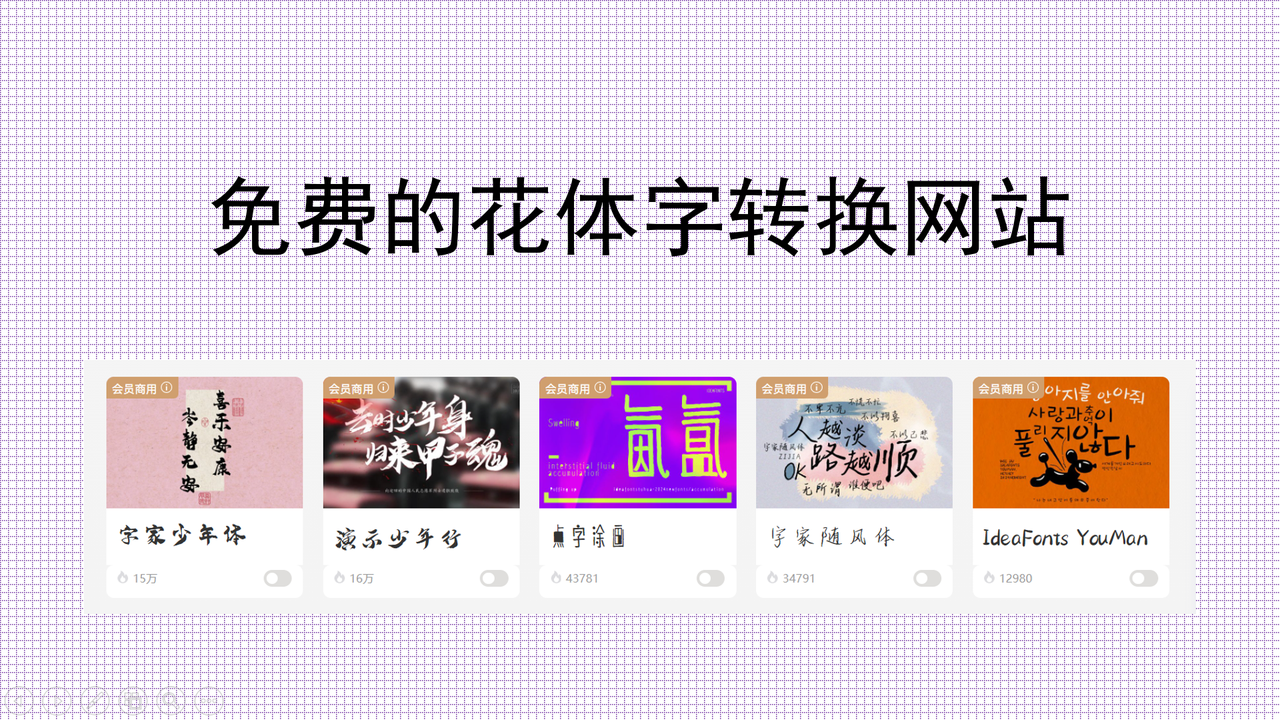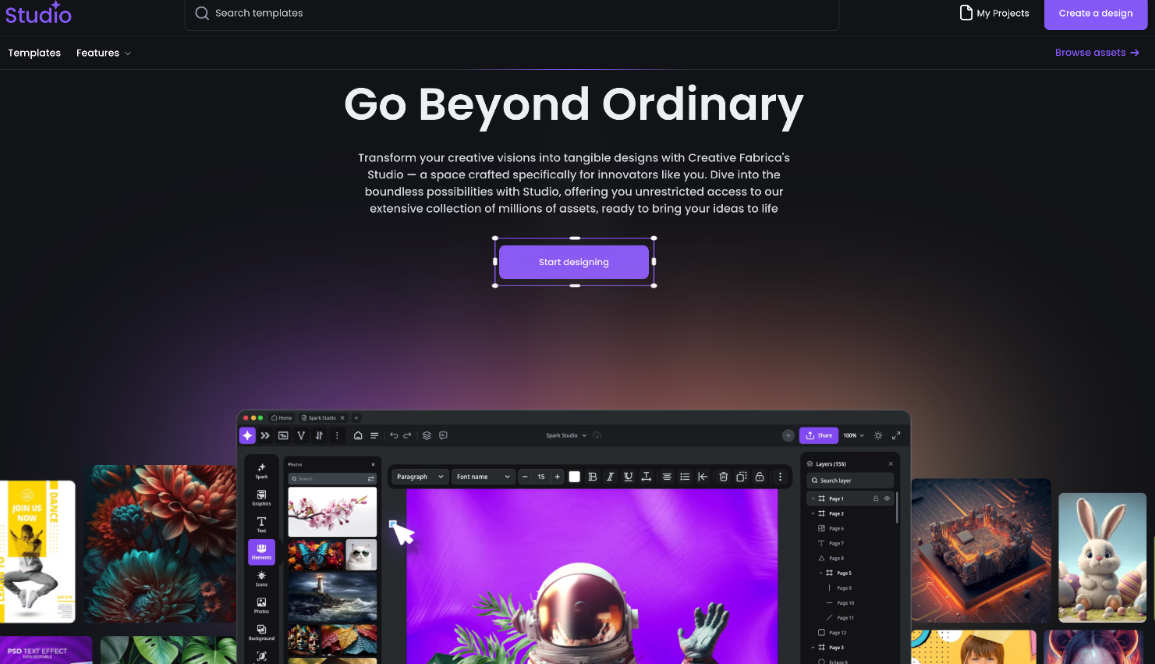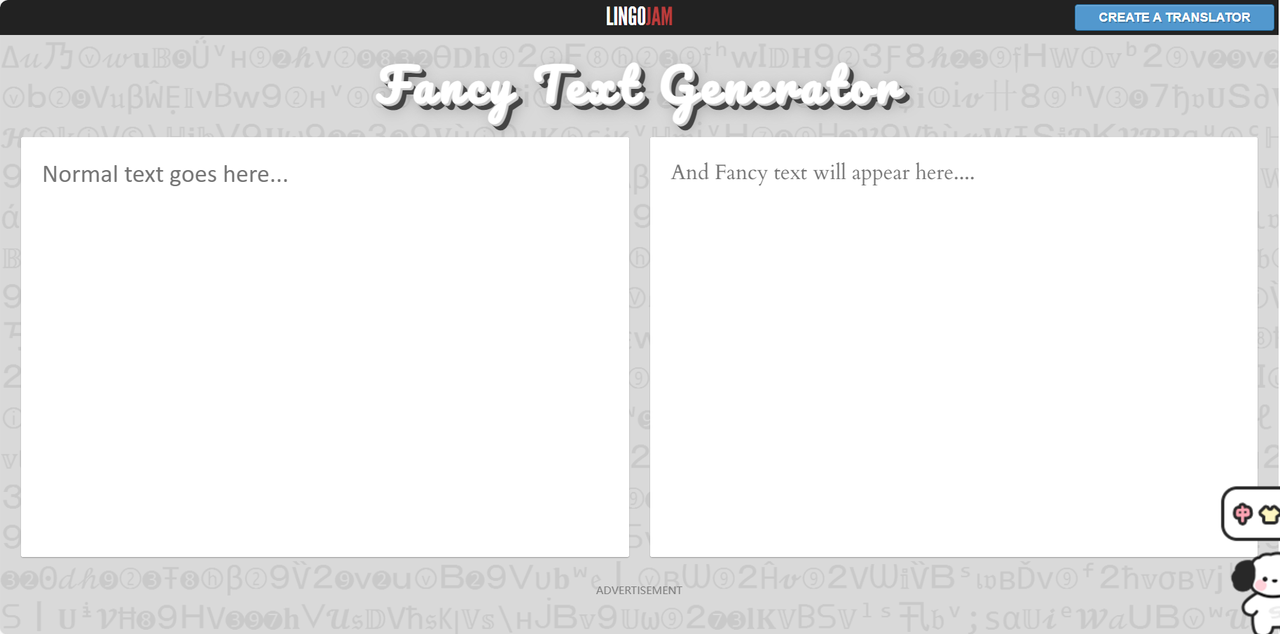
免费花体字转换网站,高颜值花体一键生成无版权
在社交媒体盛行的时代,个性化的文字表达已经成为彰显自我风格的重要方式,而选择一组美观别致的花体字总能瞬间抓住其他人的眼球。不过,很多人对于字体的认知还停留在下载安装字体包或者是学习设计字体的阶段,流程繁琐。事实上,你只需要一个免费的花体字转换网站,几秒钟内就可以将文字一键转换为高颜值花体字,生成的文字可以直接用于各类设计作品,大部分网站还保证了字体的商用版权。今天,我就来给大家推荐 5 个好用又免费的花体字转换网站,从功能特点到操作体验,全方位带你解锁快速获得花体字的方式,让你的设计告别平庸!
一、字由
作为一款专业的字体管理平台,字由不仅仅是一个花体字转换工具,更是一个集字体资源、商用版权保障、云端字库、AI 工具于一身的综合性网站,在设计行业好评如潮。字由拥有超多高颜值花体字模板,一般我会在资源库筛选“创意字体”,挑选心仪的字体模板后,再输入自定义文字内容,就可以一键转换成花体字。最让我放心的一点就是,字由上的每款字体都清晰标注了它的授权方式,不管是商用还是个人使用都可以,满足了不同用户的设计需求。
关于花体字转换,字由还有一个特别功能体现在它的客户端上。用户只需要在设计软件选中想要改变的字体文本,然后通过字由客户端可实现在 PS、AI、ID、XD、Figma、Sketch、CDR 等设计软件中一键应用字体,一秒将普通文字转换成对应的花体字效果。你再也不用全网下载安装字体包,就能完成字体应用,省去了字体查找、下载、安装的麻烦,对于经常做设计的用户来说,这个功能简直是高效率神器。
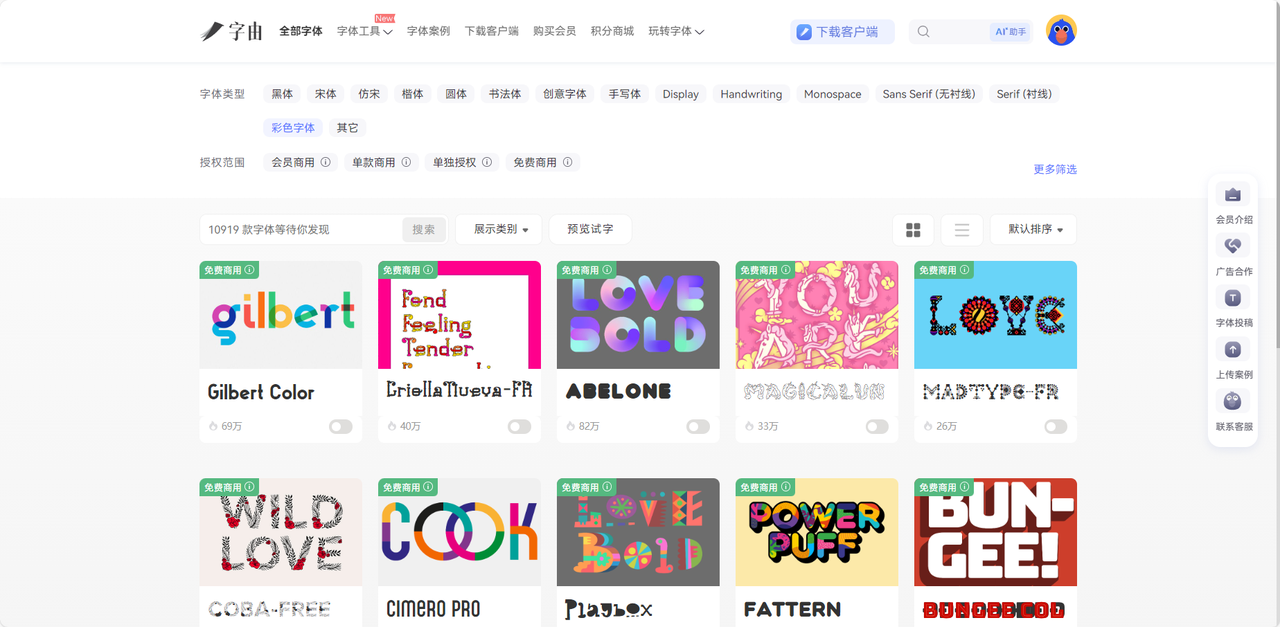
二、Creative Fabrica
Creative Fabrica 是全球知名的创意设计素材网站,但是或许很多人不知道它还是一个功能强大的面给花体字转换工具。进入它的官网首页找到对应的功能页面,只需要在文本框中输入你想要转换的文字,点击生成按钮,系统就会立刻生成多种风格的花体艺术字,你可以直接复制粘贴到其他的设计媒体平台,几乎都可以兼容,不会出现任何乱码和问号。而且它支持中英文混合生成,对于双语设计的用户来说非常友好,有需求的话可以去体验一下。与其他工具相比,其实 Creative Fabrica 最大的亮点在于资源库的丰富,汇集了海量的设计师作品,在生成花体字的时候,你还可以无缝浏览网站内的各种创意字体资源,会给你提供很多设计灵感哦。
三、LingoJam
LingoJam 在字体爱好者的圈子里有着超高的人气,它不是我们传统意义上的字体转换工具,而是一种根据字体风格单独划分的专属生成器工具。也就是说,进入 LingoJam 的首页之后,用户可以根据自己的需求选择一个风格,进入它的生成器,这样会直接生成符合当下风格的花体字。对于那些非常熟悉字体风格,也非常了解自己本次的作品需要哪种风格的字体的设计师来说,LingoJam 使用起来会更加高效,避免你在大量的字体样式中逐一浏览再挑选自己满意的字体。每个风格的字体生成器操作逻辑都是一样的,输入文字后就会立即显示转换结果,实时预览。前前后后我也尝试过 LingoJam 的很多风格了,最想给大家推荐的还复古风格的花体字生成器,是它最经典的一种,偏爱中古风格的视觉设计的小伙伴一定会爱上它!
四、FontChanger.cool
FontChanger.cool 是一个字体样式丰富且全面的花体字转换网站,涵盖了花体、粗体、哥特体、斜体、涂鸦体等多种字体,风格也是从简约到赛博朋克,你想要的这里都有。FontChanger.cool 支持一键复制字体,每个生成的花体字旁边都会有一个复制按钮,可以直接粘贴到任何支持 Unicode 的平台上使用。这一功能省去了反复切换样式的步骤,批量生成和批量复制变得异常轻松,尤其适合需要为多个不同平台准备多组花体文案内容的创作者。和 Creative Fabrica 一样,它也支持中英文混排,虽然这款工具主要是针对英文花体字进行转换,但是在中文的输入方面也做了优化兼容,呈现效果还是非常不错的。
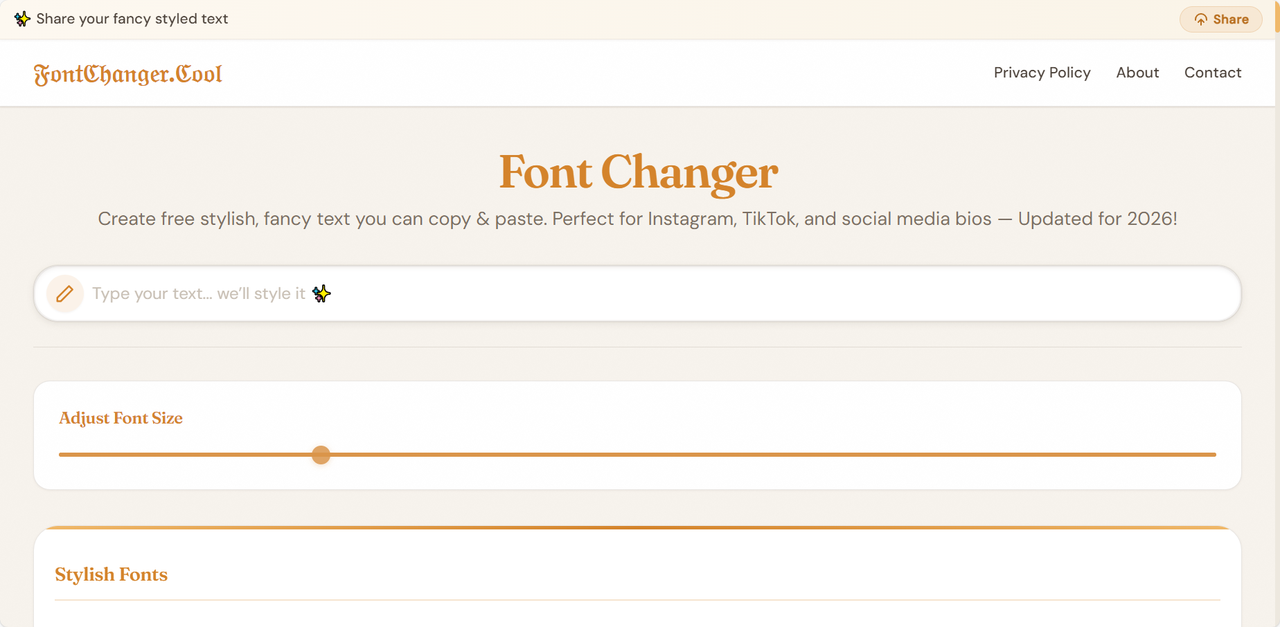
五、AuraFonts
追求前卫潮流或是极致繁复风格的花体字用户,一定不要错过 AuraFonts,它提供了超过 1000 种字体,甚至还有前卫的装饰边框、元素符号等。AuraFonts 支持批量预览,它的界面采用了动态预览设计,只要你输入文字,下方的每个样式栏都会同步刷新预览效果,非常直观。我周围很多设计师朋友都经常夸赞 AuraFonts 上面的装饰符号,普通的文字添加上这些装饰边框之后都会一秒变成高颜值艺术品,给人眼前一亮的感觉。最值得一提的是,AuraFonts 提供了大量的 Emoji 和特殊符号组合样式,可以非常自然地在文字笔画中融入小表情、爱心、星星等元素,很适合用于制作社交媒体配图、社交媒体文案签名等场景。如果你日常的设计风格比较偏向可爱风少女风,或者喜欢复杂绚丽的设计效果,AuraFonts 简直就是你的天选工具。
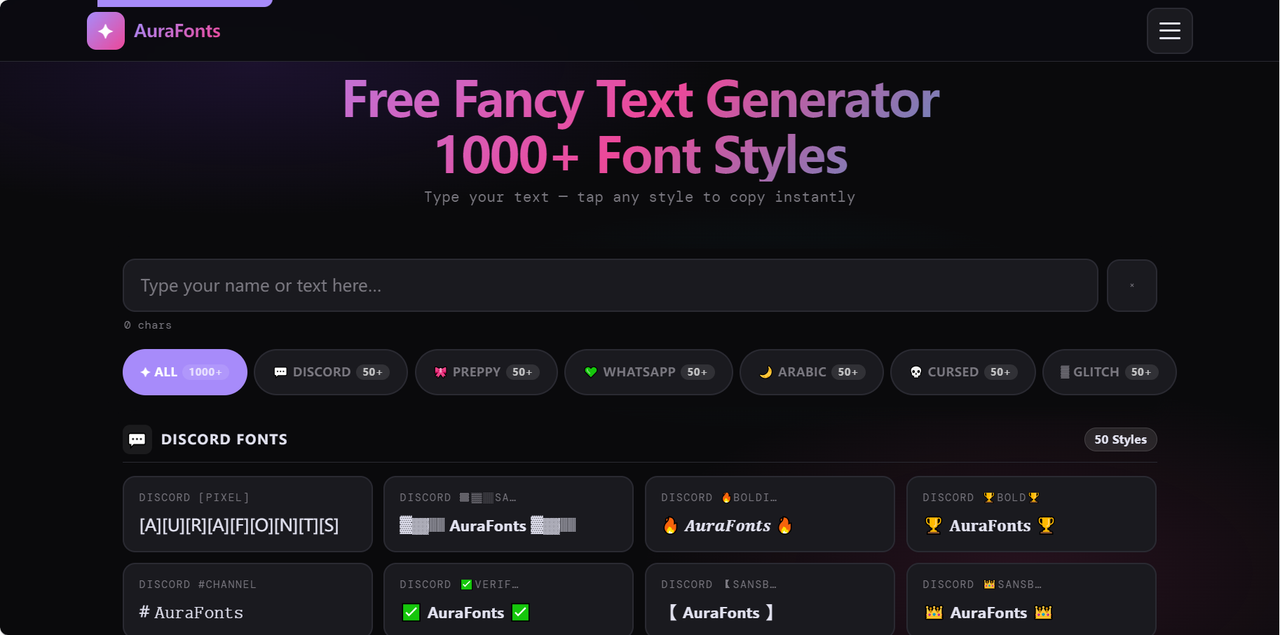
花体字作为一种视觉语言,已经是我们日常生活中非常常见的存在了,从电商产品设计到社交媒体配体,从个人签名设计到视频封面等等,每个场景都会有花体字的出现。上述给大家推荐的花体字转换网站——字由、Creative Fabrica、LingoJam、FontChanger.cool 和 AuraFonts,每一款都是我使用过后觉得体验感不错的,只是不同工具有不同的功能优势罢了,找到最适合自己的花体字创作工具才是最重要的!现在打开这些网站,一键生成高颜值花体字,打造独一无二的视觉作品吧!